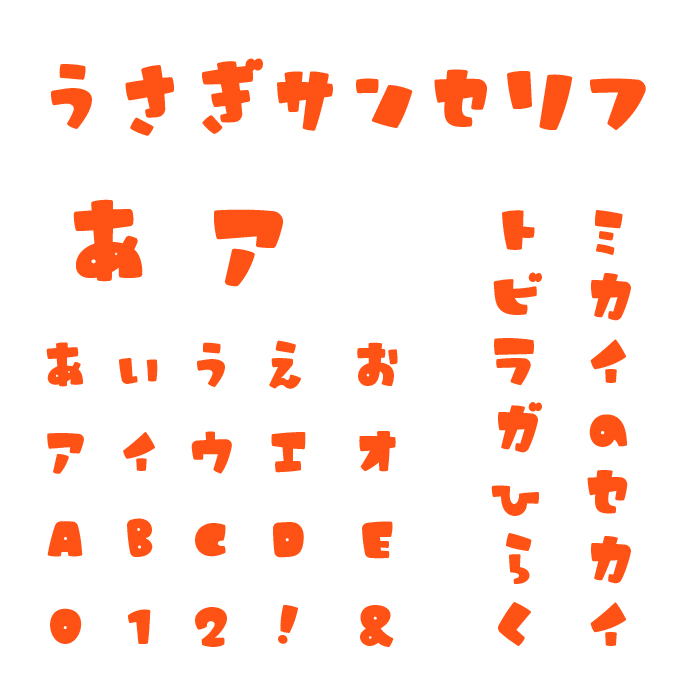
「うさぎとまんげつのサンセリフ」フォントは、うさぎの軽快な動きと満月の堂々とした安定感を兼ね備えた、個性豊かなデザインフォントです。文字の太さが一律ではなく、少しランダムな太さになっているが可愛いです。
文字は太めのウェイトで、しっかりとした動きが感じられ、視覚的にも遊びを感じる印象でありながら、安定した形状を持っています。そのため、バナー、アイキャッチ、タイトル、見出しといったビジュアルデザインに使うと、印象的でインパクトのある表現を生み出すことができるフォントとなっています。
うさぎとまんげつのサンセリフフォントの文字見本
フリー版の収録文字は、ひらがな、カタカナ、一部漢字、一部記号、英字大文字となっています。通常版では、利用可能な漢字の文字数が増えるバージョンとなっています。